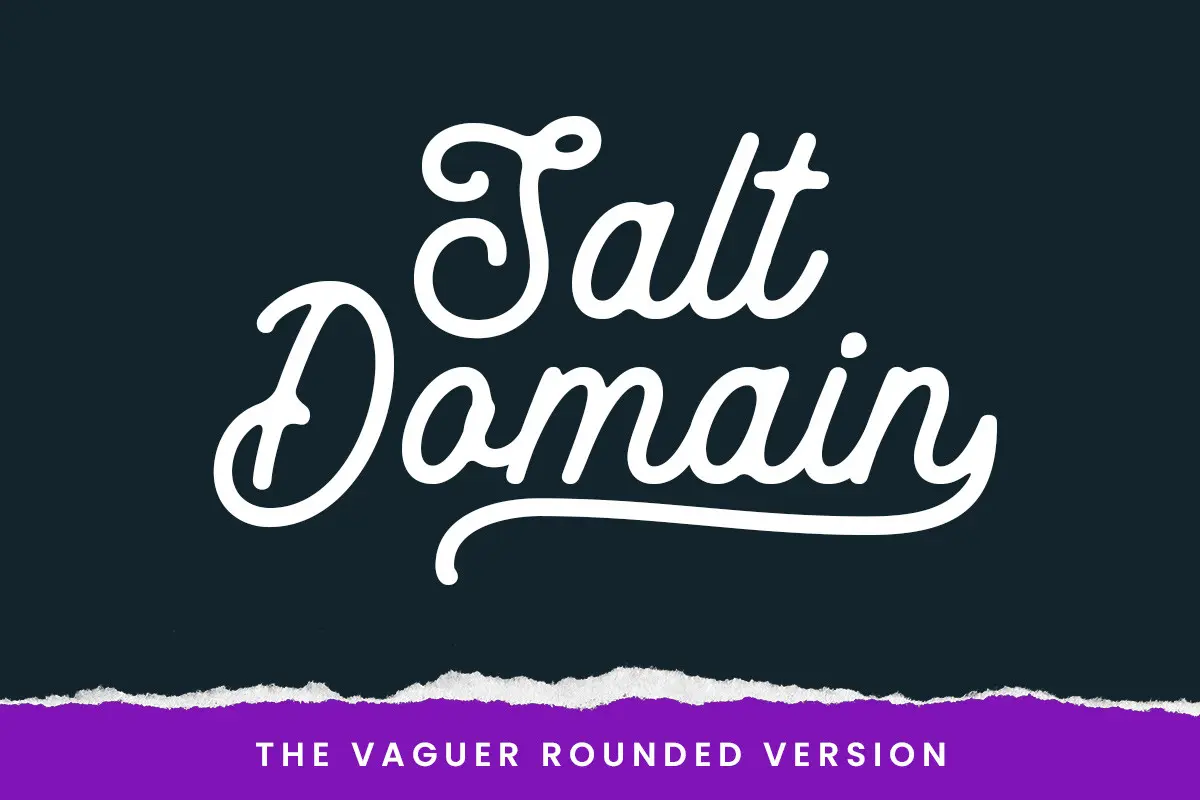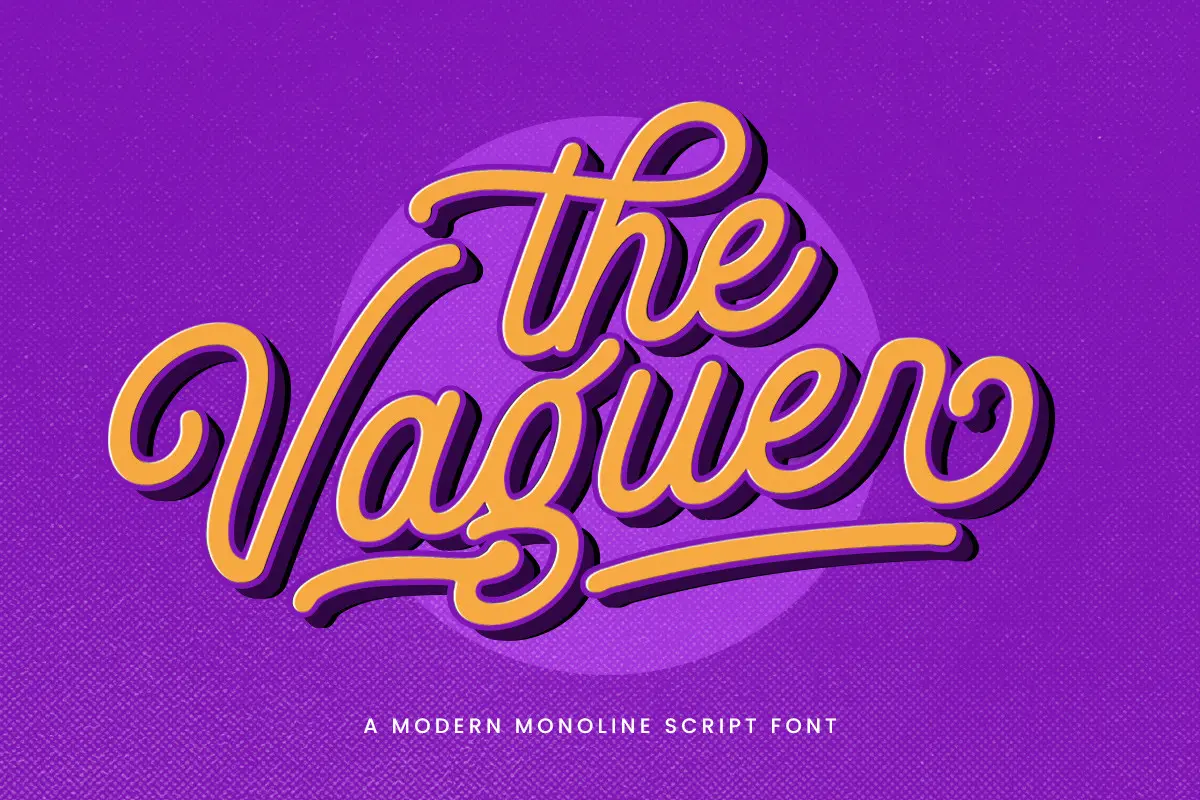
فونت اسکریپت وینتیج
Vaguer یک فونت اسکریپت زیبا، متعادل و الهامگرفته از سبکهای وینتیج است. این فونت با انحناهای نرم و روان طراحی شده و برای پروژههایی که نیاز به حس ظرافت، اصالت و جذابیت بصری دارند انتخابی فوقالعاده است. برای برندینگ مد، طراحی ادیتوریال، لوگوتایپهای ظریف، بستهبندی لوکس و پروژههای هنری کاملاً مناسب است و بهراحتی میتواند هویت بصری شما را حرفهایتر و چشمگیرتر کند.
⭐ ویژگیهای فونت
- سبک اسکریپت وینتیج با انحناهای نرم
- تعادل بصری عالی در حروف
- مناسب برای برندینگ مد و فشن
- مناسب برای طراحیهای ادیتوریال و تایپوگرافیهای ظریف
- خروجی حرفهای و قابل اعتماد در انواع پروژهها
🎯 موارد استفاده
- طراحی لوگوهای دستنویس و ظریف
- برندینگ فشن و پوشاک
- مجلات، ادیتوریالها و پوسترهای هنری
- بستهبندی محصولات لوکس
- کارت دعوت، کارت ویزیت و تایپوگرافیهای تزئینی